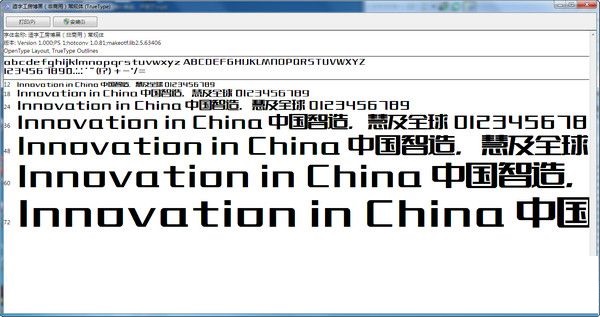
mfbohei nocommercial regular字體是一款特征鮮明的黑體字體,字型設(shè)計(jì)巧妙有新意,視覺效果出色,文字標(biāo)題、廣告設(shè)計(jì)、影視設(shè)計(jì)都用得上,需要的小伙伴快來綠色資源網(wǎng)下載吧!
1.造字工房博黑體有沉穩(wěn)雍容的靜意之美,具有極強(qiáng)的時(shí)尚感;
2.整體字形風(fēng)格厚重沉穩(wěn)、制作采用偏上的中宮方式,使其字形方挺規(guī)整;
3.主副筆畫處理清晰明確,筆畫大小極變、輕重有節(jié)、直角和圓角處理穿插,剛?cè)岵?jì);
4.此款字體適用于文字標(biāo)題、廣告設(shè)計(jì)、企業(yè)宣傳及時(shí)尚品牌的設(shè)計(jì)應(yīng)用,有著極強(qiáng)的應(yīng)用空間。